Kenapa Semua MEME di Internet Menggunakan Font yang Sama?!
IntermezzoKenapa Semua MEME di Internet Menggunakan Font yang Sama?! - Tampaknya kini Meme dan gambar-gambar lucu sudah mendominasi internet ya. Dikit-dikit ada Meme, pengen buka website tertentu, eh ada Meme-nya, dan berbagai kasus lainnya yang membuktikan bahwa meme sudah menjadi bagian dari aktifitas berinternet kita sehari-hari. Tapi apakah kamu menyadari bahwa bentuk standar dari Meme itu terdiri dari gambar dan tulisan yang berada di bagian atas dan bawah. Template yang monoton tersebut sebenarnya dimulai dari mana sih, dan kenapa harus menggunakan font yang sama untuk jutaan Meme di luar sana?
Melalui artikel ini, akan kami kupas tuntas, dari mana asalnya sehingga meme menggunakan satu font yang sama. Baca terus artikel ini hingga habis ya.
Impact, Font Jadul yang Mendominasi Dunia Internet
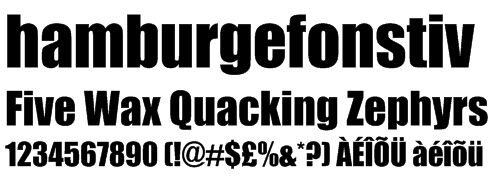
Oke, mari kita langsung to the point, font yang sering kamu temukan di setiap meme yang beredar di internet itu bernama Impact, dan ia rupanya sudah hadir jauh sekali sebelum adanya era dunia maya. Impact merupakan font yang diciptakan oleh Geoffrey Lee pada tahun 1963. Ia menciptakannya dalam tiga jenis yang berbeda, meliputi Bold, Condensed, dan Sans Serif. Semua itu sesuai dengan gaya pop yang sedang hits sekali di tahun 1960-an, yang menekankan kepada font headline yang tegas dan dapat digunakan di berbagai poster dan iklan.
Geoffrey sebenarnya terinspirasi dari font-font yang diiptakan oleh gerakan bernama The International Typographic Style, atau dikenal dengan nama SWISS Style. Impact mengikuti font-font karya dari Swiss Style seperti Helvetica dan Univers yang dirancang memang untuk mudah dibaca dan bersih. Impact yang populer tersebut akhirnya dijual kepada perusahaan Stephenson Blake, melalui plat-plat besi ukiran untuk percetakan.
Semakin Tenar Akibat Ulah Microsoft
Setelah berjaya melalui Stephenson Blake, Impact kemudian dijual kembali kepada salah satu perusahaan typeface terkemuka lainnya yaitu Monotype. Jika ketika kamu mengetik menggunakan Microsoft Office, pasti tidak akan lepas dari font bernama Times New Roman kan, dan Monotype lah pemilik dari font legendaris tersebut. Melalui kerjasama lisensi yang terjalin di antara Monotype dan Microsoft, maka beberapa font milik Monotype pun akhirnya muncul di produk-produk Microsoft, tentu saja salah satunya adalah Impact.
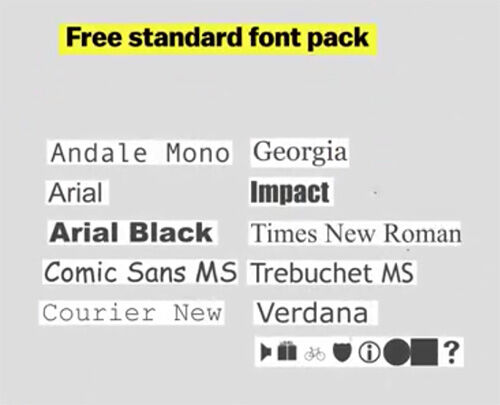
Pada tahun 1996, Microsoft membuat satu standar terhadap font yang digunakan pada website-website yang beredar, mereka menamakannya sebagai 11 core fonts, atau Free Standard Font Pack. Mudah ditebak, salah satu font yang ada di dalam paket tersebut tentu saja ada Impact. Dari sinilah awal dari populernya beberapa font di kalangan pengguna internet, terutama font Impact yang sangat digemari oleh pengguna forum di dunia maya.
Meme Cinta Impact
Sudah tidak dapat dipungkiri lagi bahwa Meme merupakan salah satu senjata pamungkas dari para pengguna forum yang tersebar di internet. Demi memudahkan pembuatan Meme sehingga menjadi terstandardisasi, maka dibutuhkan satu alat yang dapat memudahkan pembuatan media ekspresi tersebut. Maka muncullah jenis image macros, yaitu Meme yang berdasarkan kepada instruksi otomatis yang sebelumnya telah diatur sedemkian rupa sehingga pengguna hanya perlu meng-input step sederhana untuk menciptakan Meme.
Awal dari meledaknya Meme ada di tahun 2003. Pada tahun tersebut, internet dihebohkan dengan foto kucing lucu yang bertuliskan ** I CAN HAZ CHEEZBURGER **. Tebak font apa yang digunakan untuk menuliskan pernyataan tersebut? Yap benar, Impact. Semenjak saat itu situs-situs yang menyediakan meme generator mulai bermunculan guna mempermudah orang-orang dalam menciptakan Meme nya sendiri. Kini bahkan aplikasi Android untuk membuat Meme ikonik tersebut pun sudah banyak beredar lho.